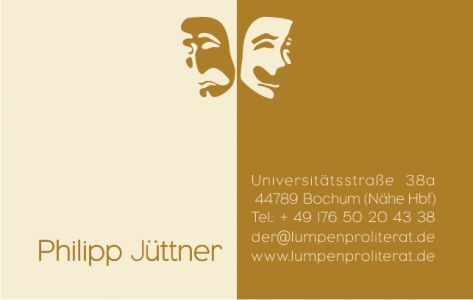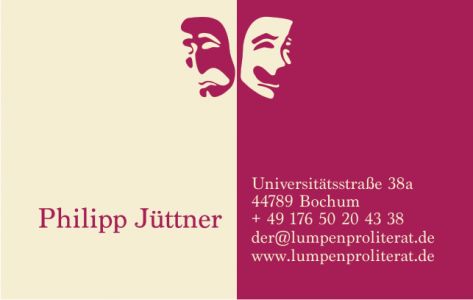
... klar kann Theater alles sein, und bürgerliche Kritik war und ist sicherlich stets auch Anliegen und Aufgabe des Schauspiels! Insofern unterliegt auch die Gestaltung einer dbzgl. Visitenkarte keinerlei Reglement -- oder zumindest weit weniger als bei anderen Berufen/Branchen.
Und so ist das auch mit den Assoziationen in Sachen Theater. Da geht fast alles (Himmel, ich geriet einst in eine Inszenierung des FAUST, in der der Mephistopheles von einer Dame in Strapsen und SS-Dienstmütze gespielt wurde ... unverzeihlich war übrigens lediglich ihre piepsige Stimme) und das ist auch gut und richtig so. Mir persönlich gelingt der Brückenschlag Gefahrenschild--Theater nicht, was nun gar nicht heißen soll und kann, dass der unmöglich sei!
theater ist aber nicht gleich theater und was hey genau macht wie »abgefahren« es sein kann wissen wir nicht, ich denke nur, dass er nicht so sehr den »traditionelen« theater macht, von daher ist seine sicht verständlich.
... sehe ich ähnlich: die Verbindung Kultur und Gefahrenschild leuchtet mir auch nicht sofort ein. Die lachende/weinende Maske ist eher ein "Theaterzeichen" und zudem ein recht oft Bemühtes. Da gibt es sicherlich etwas Originelleres? Vielleicht eine als Bühne gestaltetes Visitenkarte, so mit Vorhang ... und die Daten, wie eine Art Kinoabspann, so mit Punktlinien dazwischen? Doch das wär wahrscheinlich schon wieder etwas zu viel Impression, keine Ahnung! Kommt freilich wieder sehr auf die Leutchen an, insofern wird es der Philipp sicher besser wissen.
In der Tat ist es umgekehrt: die Theatermasken habe ich schon lange nicht mehr gesehen, Vorhänge, Kinoabspannmäßiges sehe ich dagegen ständig in Theaternahen Druckwerken. Zu originelle Grafiker ? :twisted:
Ach wenn mich gerade Eure letzten Beiträge eher in Richtung Warnschild tendieren lassen, hier noch zwei gemäßigte Entwürfe:
Schade. Durch die Trennung in Positiv-/Negativ-Darstellung sehen nun beide Gesichter sehr traurig aus. Das ist schon depremierend :cry:
Ach wenn mich gerade Eure letzten Beiträge eher in Richtung Warnschild tendieren lassen, hier noch zwei gemäßigte Entwürfe:
Schade. Durch die Trennung in Positiv-/Negativ-Darstellung sehen nun beide Gesichter sehr traurig aus. Das ist schon depremierend :cry:
Ach, das passt schon. Einige der lustigsten Stücke deutscher Zunge bezeichnen sich selbst ja als »bürgerliches Trauerspiel«. :wink:
Ach wenn mich gerade Eure letzten Beiträge eher in Richtung Warnschild tendieren lassen, hier noch zwei gemäßigte Entwürfe:
find ich zu brav und zu kitschig. gefällt mir nicht.
Flagge weg, Linie raus, Unger-Fraktur rein,
mir fallen keine Superlative ein.